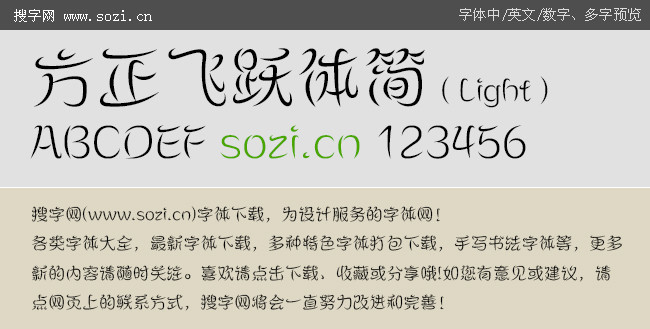
方正飛躍體簡Light
搜字網(wǎng)提供一款方正飛躍體簡中文字體下載,方正飛躍體簡是一款充滿活力和跳躍的中文字體,該字體特點是沒有直線,全是弧線組成,橫劃都向右上角斜上,頭部有一個彎鉤,所有撇,捺,點都用弧線形表達(dá),因此增強飛躍體的感覺,適合應(yīng)用于包裝設(shè)計、平面設(shè)計、網(wǎng)頁設(shè)計、海報設(shè)計等應(yīng)用。